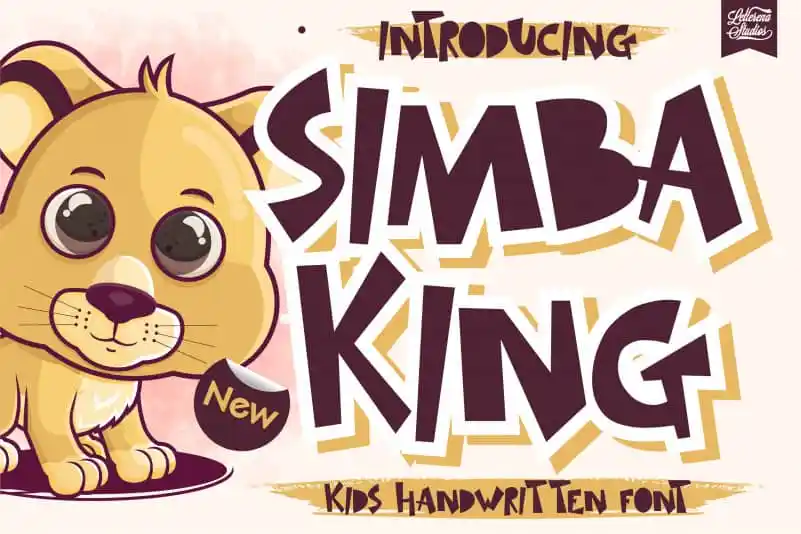
Simba King Display Font – Fonte Grátis
Simba King Display Font
A fonte ‘Simba King Display Font’ é uma opção ideal para quem deseja dar vida aos materiais digitais com alegria e versatilidade. Desenvolvida pelo designer letterenastudios, ela carrega um toque animado e descontraído que remete ao estilo de desenho animado de forma inconfundível. Com seu formato amplamente adaptável, é perfeito para usar em qualquer contexto – desde cartazes promocionais até designs web dinâmicos. Suas nuances charmosas e um toque alegre garantem uma presença visual divertida e eficaz em qualquer projeto. Seja você criador de conteúdo, designer gráfico ou simplesmente alguém que adora personalizar sua identidade digital com estilo, ‘Simba King Display Font’ é uma opção segura para tornar seus projetos ainda mais memoráveis.